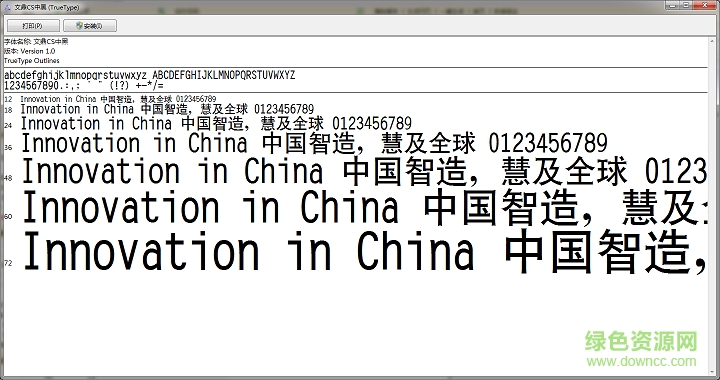
heiticseg-medium-gb字体
heiticseg-medium-gb是什么字体?heiticsegmediumgb字体又叫文鼎CS中黑字体,字体结构规范,简洁无装饰,多用于印刷、文本标题等领域,也可用作正式场合的书面报告字体!
黑体字介绍
黑体字是现代汉字体系中最重要的字体之一。尤其是随着20 世纪末电脑和互联网的普及,黑体字的价值得到了进一步体现,它简洁的笔画特征与屏显介质特性相符,从而成为了当今各种屏幕媒介中最有发展前景的无衬线字体